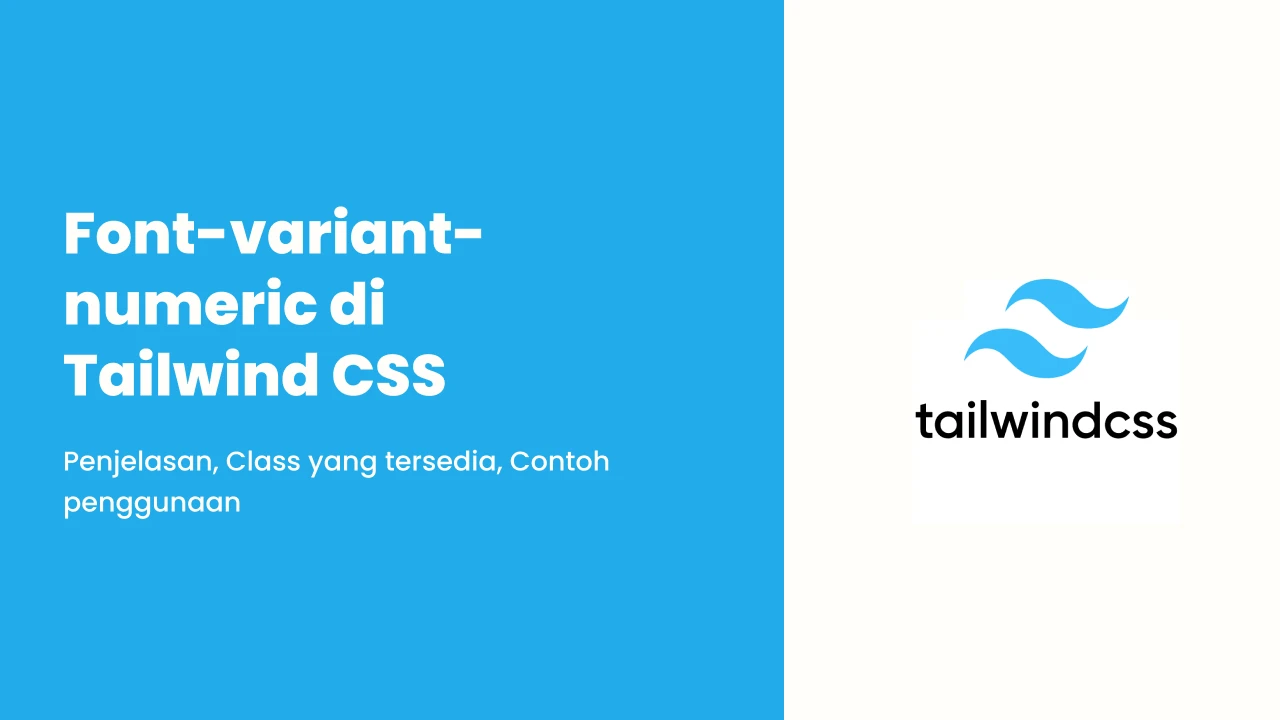
Belajar Tailwind CSS #85 Font-variant-numeric di Tailwind CSS
Apa itu font-variant-numeric?
Ini adalah utility di Tailwind CSS yang digunakan untuk mengatur gaya tampilan angka (numeric glyphs) di elemen teks. Fitur ini tergantung pada dukungan dari font yang digunakan.
Kelas & Fungsinya:
|
Class |
Fungsi |
|
normal-nums |
Mengembalikan tampilan angka ke gaya normal (default). |
|
ordinal |
Menambahkan gaya khusus untuk angka berurutan, seperti "1st", "2nd", dll. |
|
slashed-zero |
Menampilkan angka nol dengan garis miring (contoh: 0̸). |
|
lining-nums |
Menyusun semua angka sejajar di garis dasar (baseline). |
|
oldstyle-nums |
Menyusun angka seperti huruf kecil, sebagian turun ke bawah garis dasar. |
|
proportional-nums |
Angka memiliki lebar berbeda tergantung bentuk (seperti huruf biasa). |
|
tabular-nums |
Semua angka punya lebar yang sama, cocok untuk angka sejajar seperti tabel. |
|
diagonal-fractions |
Menampilkan pecahan seperti ½, ¾ secara diagonal. |
|
stacked-fractions |
Menampilkan pecahan seperti ½, ¾ dalam bentuk vertikal (stacked). |
Contoh Penggunaan:
1. Angka Berurutan (Ordinal)
berikut hasilnya:
2. Nol dengan Garis Miring (Slashed Zero)
berikut hasilnya:
3. Angka Sejajar di Dasar (Lining Numbers)
berikut hasilnya:
4. Angka Gaya Lama (Oldstyle Numbers)
berikut hasilnya:
5. Lebar Angka Proporsional
berikut hasilnya:
6. Lebar Angka Sama (Tabular)
berikut hasilnya:
7. Pecahan Diagonal
berikut hasilnya:
8. Pecahan Vertikal (Stacked)
berikut hasilnya:
Kombinasi Beberapa Kelas
Kamu bisa menggabungkan beberapa kelas:
berikut hasilnya:
Reset & Responsif
Reset ke default:
<p class="slashed-zero tabular-nums md:normal-nums">